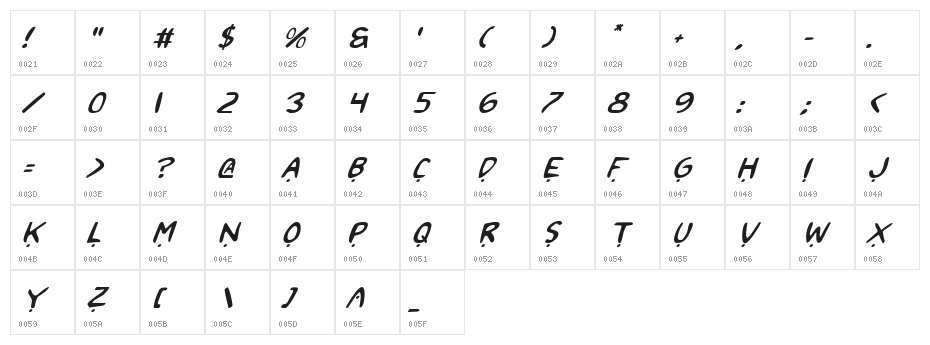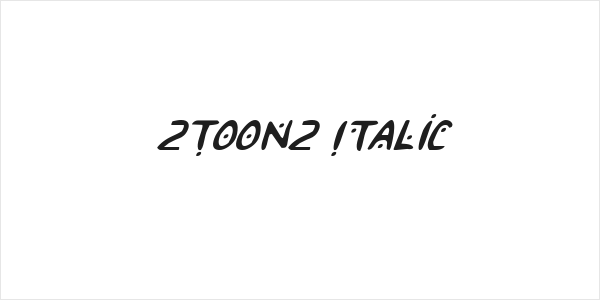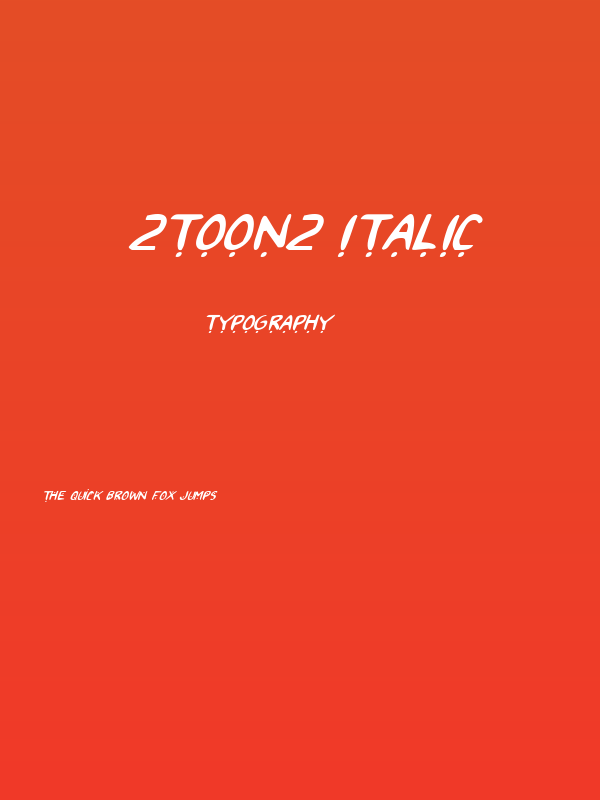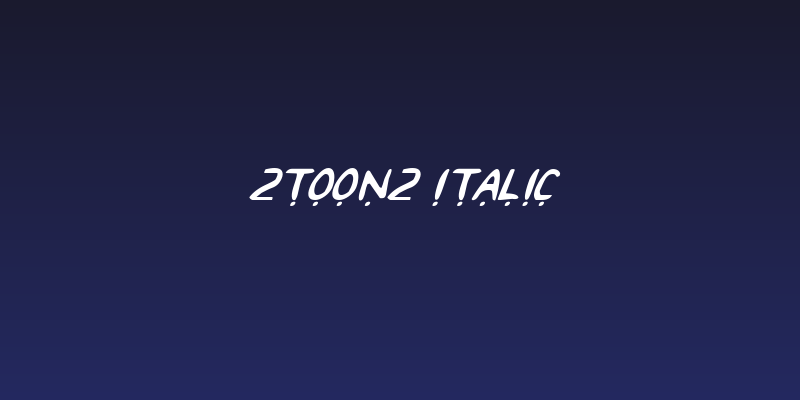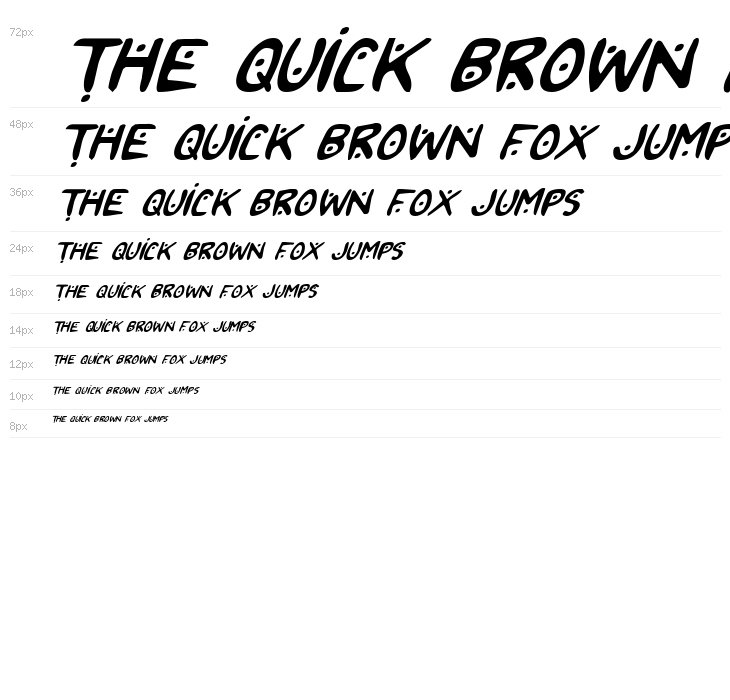
2Toon2 Italic Font
| Stile generale | Playful, Cartoonish, Dynamic |
| Progetti proposti | Ideal for comic books, children's books, playful branding, and creative posters. |